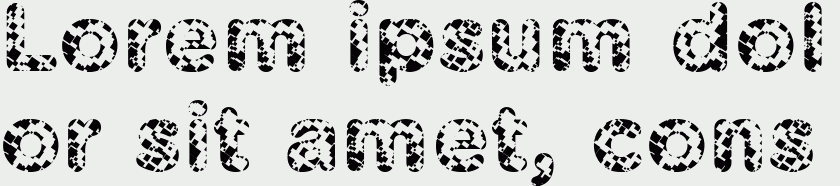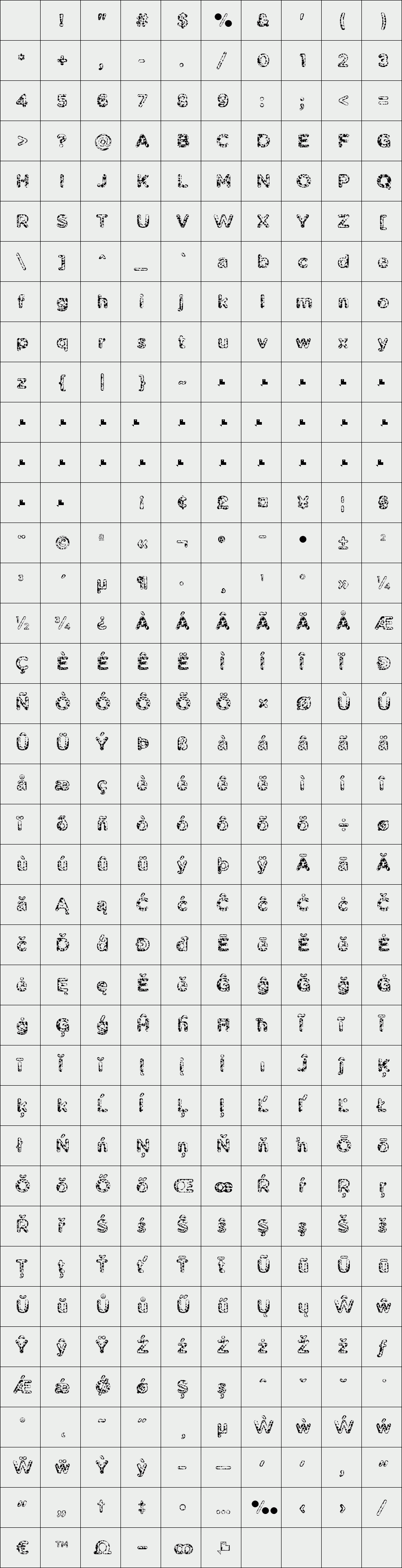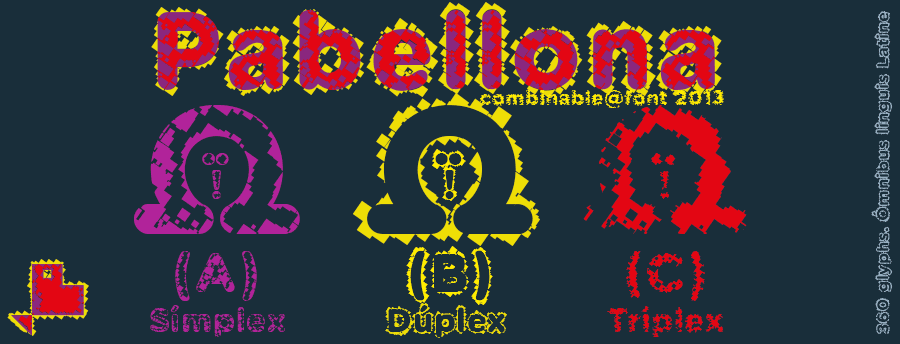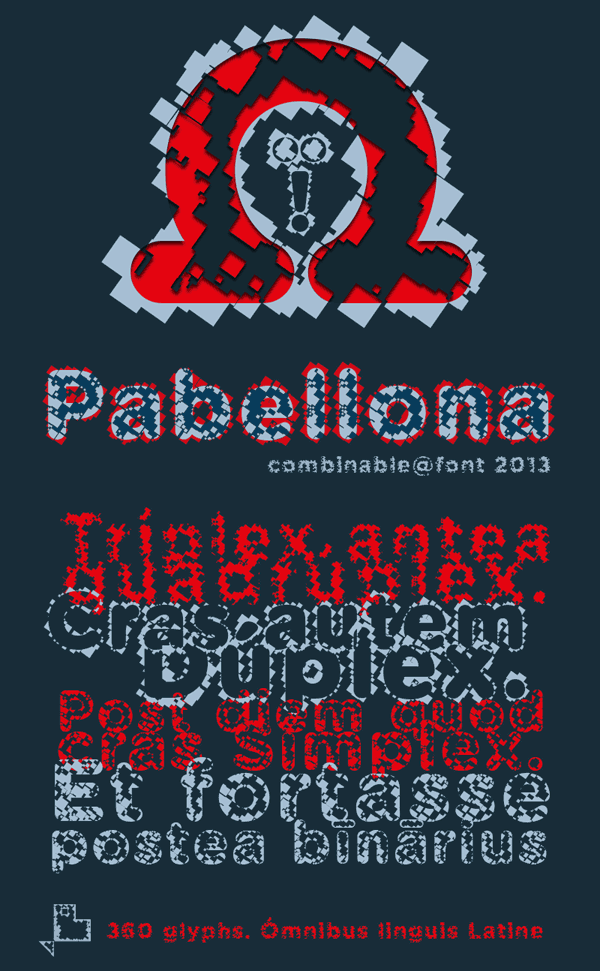
Pabellona
/ Pabellona (A) Símplex
Pabellona es un conjunto tipográfico de 3 fuentes experimentales, combinables entre si para crear textos policromados.